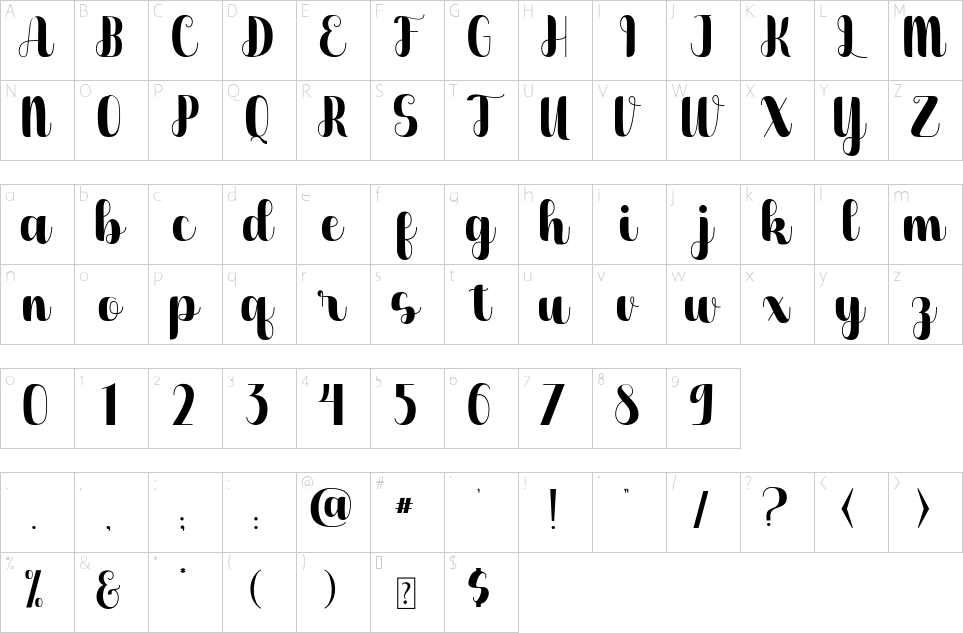
Descubra a Dilaney Font, uma opção gratuita para designers amadores e profissionais que valorizam estilo e simplicidade. Desenvolvida por StringLabs, esta fonte oferece um leque de caracteres elegantes e versáteis, adequada tanto para textos legíveis quanto para estilos gráficos mais elaborados. Se você busca uma fonte minimalista mas ainda assim com um ar distintivo, a Dilaney é perfeita. Seu design limpo e sofisticado permite que as letras fiquem em destaque de maneira suave, sem perder o caráter único presente em qualquer projeto visual. Comumente usada para textos de negócios ou anúncios digitais, esta fonte também se adequa perfeitamente a criações gráficas e tipografias artísticas. A Dilaney foi projetada por StringLabs, um grupo especializado em fontes criativas, e tem sido popular entre os designers que buscam uma opção de alta qualidade sem o compromisso do custo. Seja para fins pessoais ou profissionais, a Dilaney é uma ótima escolha para quem valoriza tanto a estética quanto a funcionalidade em suas criações digitais.